Quanto mais IA no design, mais valiosa fica a tipografia
Tipografia personalizada pode se tornar diferencial competitivo em um mercado dominado por IA
A Anthropic acaba de anunciar o Claude Design, uma ferramenta que permite que equipes gerem e refinem peças visuais por meio de comandos em linguagem natural.
À primeira vista, é difícil não gostar da proposta: layouts e tipografia competentes sob demanda, menos momentos de bloqueio diante da página em branco e mais velocidade para lançar desde landing pages até apresentações de vendas.
Quando o assunto é tipografia, a ferramenta promete tornar o design mais rápido, fácil e barato. O problema é que ela também torna o design mais propenso à convergência, porque privilegia aquilo que funciona: o que é legível, familiar e comprovado. Em outras palavras: seguro, funcional e genérico.
Essa “genericidade” não é apenas um problema estético. Ela reduz reconhecimento, torna as marcas mais fáceis de imitar e obriga empresas a gritar mais alto apenas para serem lembradas, aumentando a dependência de investimento em mídia para chamar atenção.
Um estudo realizado há alguns anos pela JKR e pela Ipsos mostrou que apenas 15% dos ativos de marca analisados eram realmente diferenciados.
A falta de diferenciação enfraquece o poder de precificação das marcas, forçando-as a competir por preço em vez de valor. Segundo a Kantar, a diferença é o principal fator que permite a uma marca cobrar mais caro dentro de sua categoria.
Em um mundo no qual as barreiras para construir uma marca nunca foram tão baixas, a concorrência é feroz e a atenção do consumidor cada vez mais fugaz, parecer igual a todo mundo deixou de ser uma opção. Na prática, a diferenciação se tornou essencial para impulsionar crescimento.
Só que isso também representa uma enorme oportunidade: se a IA empurra mais marcas para os mesmos padrões “bons o suficiente”, as empresas que investirem em uma identidade tipográfica realmente distinta vão se destacar mais depressa.
Tipografia é infraestrutura de marca. Ela precisa funcionar de maneira consistente em diferentes produtos e plataformas, escalar globalmente, dar suporte a múltiplos idiomas e, ao longo do tempo, tornar-se sinônimo da própria marca.
É justamente por isso que ela é um ponto tão estratégico: aperfeiçoar o sistema tipográfico significa aprimorar simultaneamente uma enorme quantidade de pontos de contato.
O PROBLEMA DOS PROMPTS
Isso não é um argumento contra o uso de ferramentas como o Claude Design para tipografia. Essas plataformas oferecem fontes gratuitas extremamente utilizáveis (geralmente sem serifa), funcionando como uma base bastante útil.
Mas, quando o objetivo é criar um ativo diferenciado e duradouro, recorrer a uma ferramenta que trabalha apenas com um conjunto limitado de padrões familiares e fontes amplamente disponíveis não basta.
O resultado tende a ser uma proliferação de marcas cuja tipografia é apenas uma derivação das fontes gratuitas mais populares, carregadas bilhões de vezes e presentes em milhões de sites.
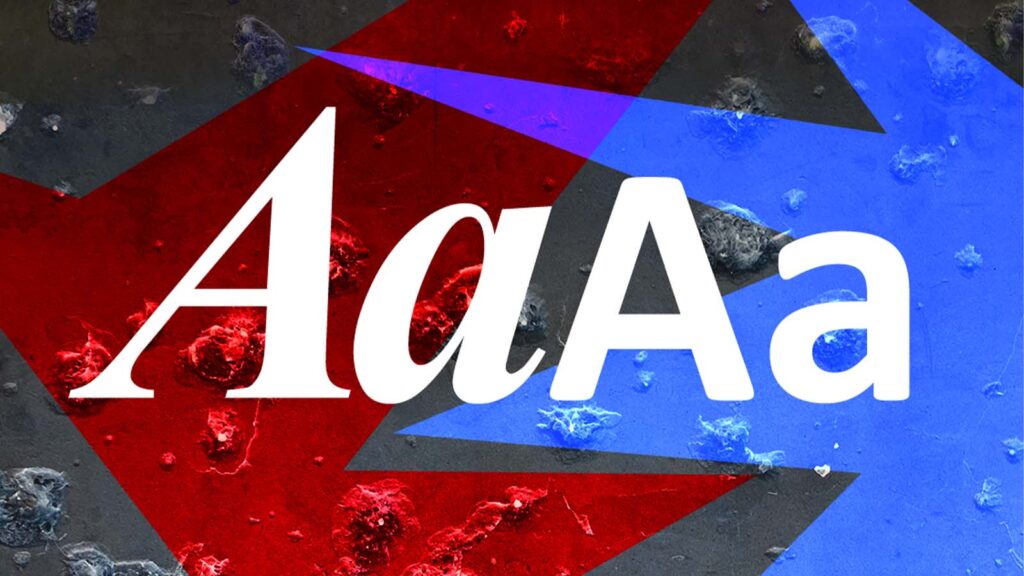
Enquanto este texto era escrito, a Roboto havia sido exibida 63,1 bilhões de vezes na semana anterior, aparecendo em mais de 410 milhões de websites. Imagine escolher um logotipo sabendo que ele é compartilhado por milhões de outras marcas.
Jamais aceitaríamos esse nível de uniformidade para um símbolo visual. Ainda assim, a tipografia frequentemente recebe um “passe livre”, mesmo sendo responsável por grande parte do trabalho pesado em inúmeros pontos de contato de marca.
FONTES CUSTOMIZADAS
No fim das contas, o Claude Design é um alerta bem-vindo: ele obriga empresas a prestar mais atenção ao poder da tipografia customizada. É importante é refletir sobre o que uma tipografia exclusiva pode representar para a marca e explorar diferentes caminhos para alcançar distinção tipográfica.
É possível criar uma “fonte-logotipo” reconhecível mesmo sem o símbolo visual, da mesma forma que algumas empresas conseguem ser identificadas apenas pelo estilo de seus títulos, como a Dunkin'.
Ou incorporar elementos diferenciados de ativos já existentes diretamente nas letras – pequenos detalhes que conectam discretamente tudo à marca.
aperfeiçoar o sistema tipográfico significa aprimorar, ao mesmo tempo, vários pontos de contato com o público.
A Everyday Sans, do Walmart, por exemplo, é uma família tipográfica proprietária criada para equilibrar expressão e funcionalidade. Suas formas são elegantes e modernas, mas preservam algumas peculiaridades únicas do logotipo da empresa, como contraformas em formato de gota, diagonais marcantes e elementos circulares alongados.
Basta olhar para as fontes usadas nos títulos de algumas das maiores empresas do mundo, como Apple, Uber e Pinterest. Retire o logotipo e as cores e fica difícil diferenciá-las. Sem distinção, sem personalidade.
Ironicamente, as ferramentas de design baseadas em IA talvez sejam justamente aquilo que finalmente colocará fim a essa “aflição”, ao tornar a originalidade mais impactante do que nunca.